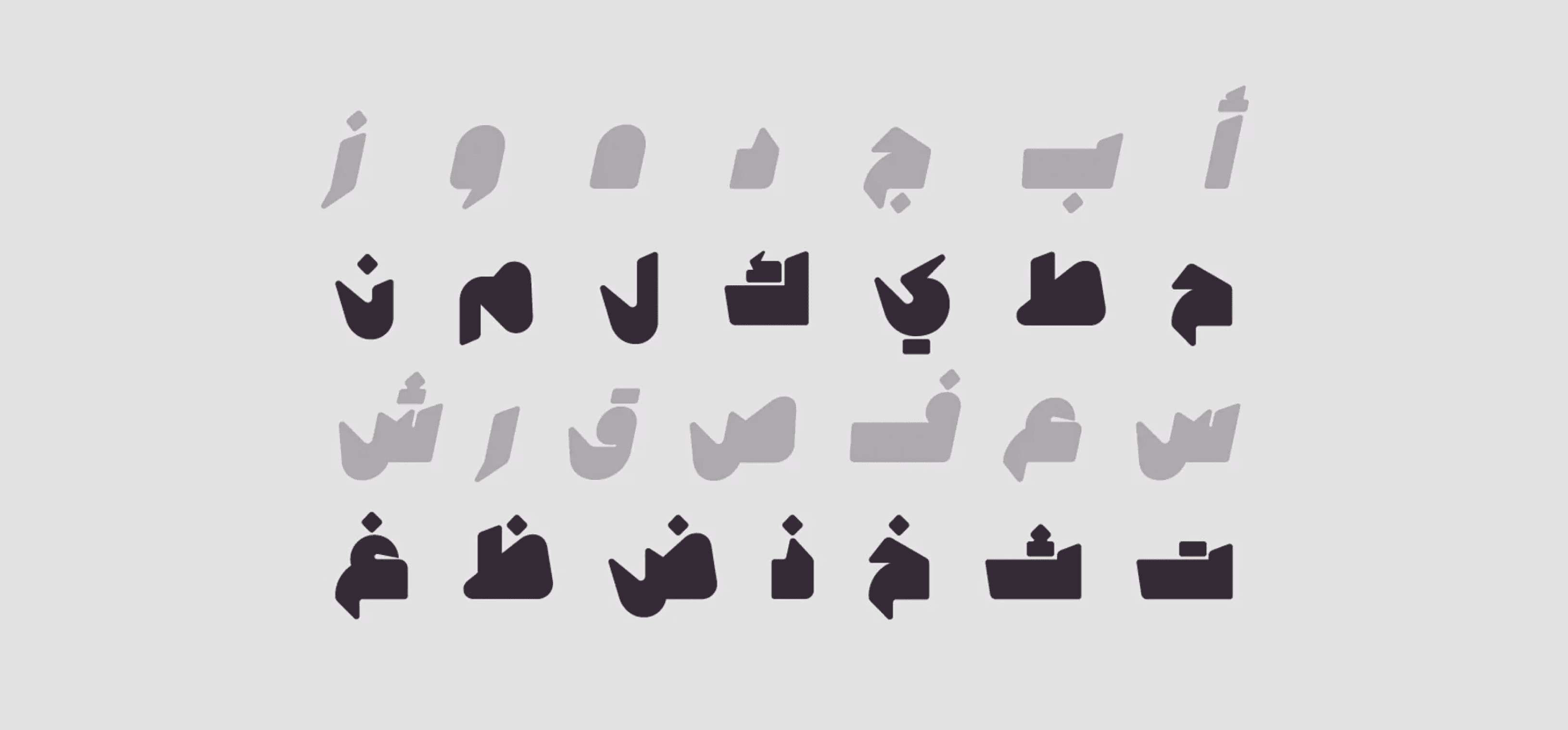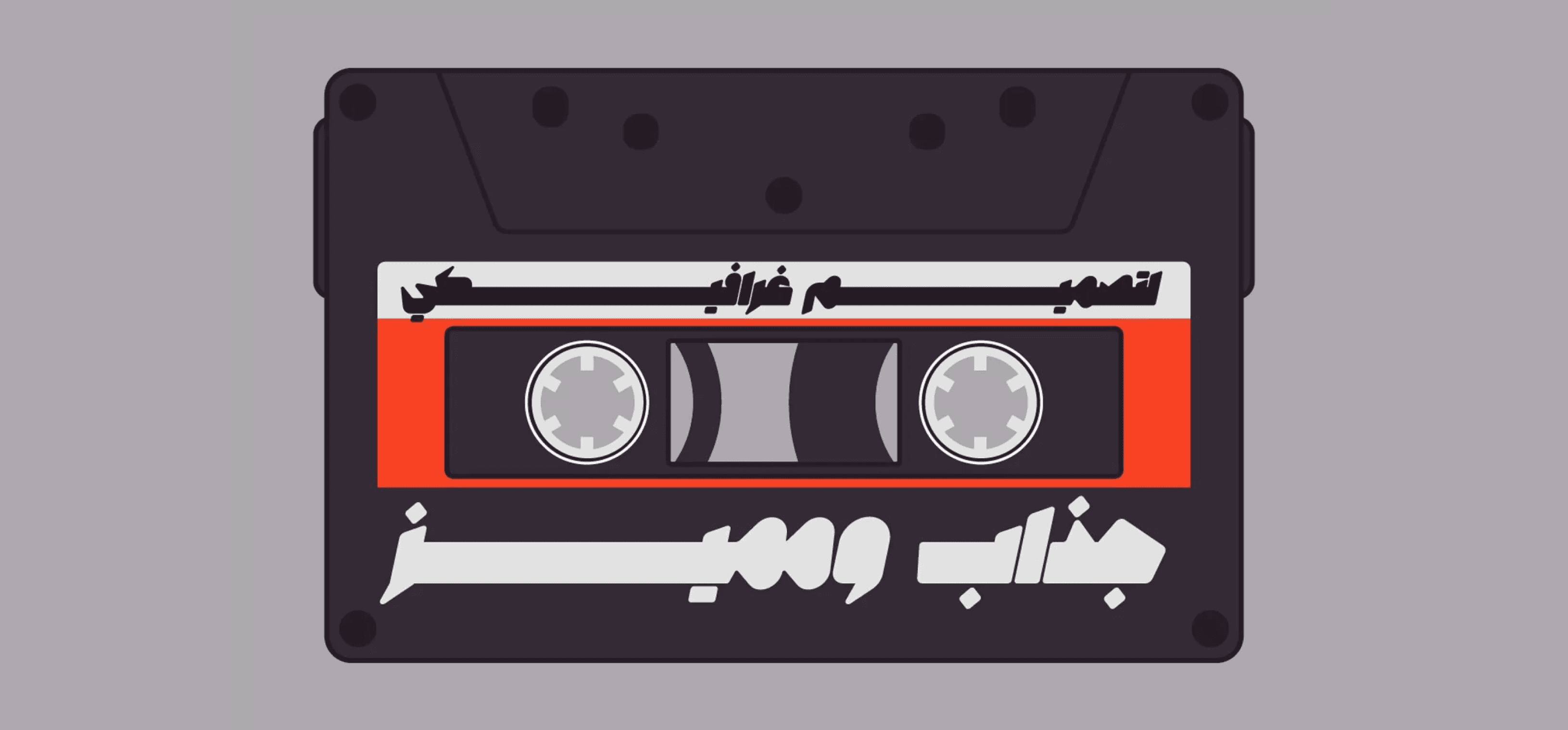
خط Marmooz (وهي كلمة عربية تعني "مُرمّز" أو "ذو رمزية") هو خط عرض عربي يتميز بأسلوب زخرفي مميز ولافت. تتكون عائلة Marmooz من خطين منفصلين بنمطين مختلفين لأشكال الحروف: الناعم (Soft) والحاد (Sharp).